なぞるだけで美文字! ペン字書き込み練習帳
■ペン字も筆ペンもこの1冊で上達する!
本書では、ペン字の上達に欠かせない「運筆リズム」の習得のために、
筆ペンのお手本を多数掲載しています。さらに、少ない練習量でも確実に
上達できるコツを丁寧に解説しました。
正しく美しい文字は、自信と信頼につながります。本書で「一生の宝物」である
美文字を身につけてください。
■日常で、仕事で、よく使う表現で練習できる
ハガキ、手紙、一筆箋、のし袋など日常生活で、また、履歴書、領収書、
振込伝票などビジネスシーンで、手描きする機会の多いものを厳選し、
お手本を掲載しました。知っておくと役立つマナーや豆知識も適宜紹介しています。
■180度開く製本で、書き込みやすい!
書き込みやすさに配慮し、180度開く製本方式を採用していますので、
ストレスなく、練習することができます。
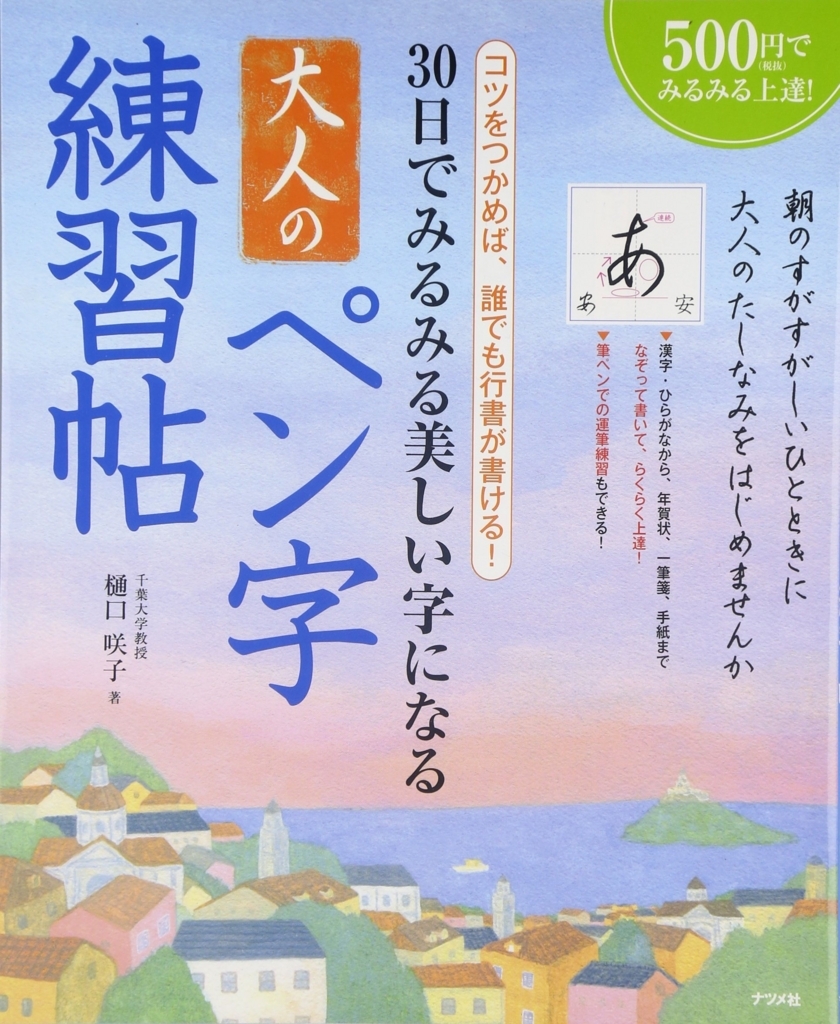
こちらも500円(税別のためワンコインではない)で美文字を練習できる「30日でみるみる美しい字になる大人のペン字練習帖」はナツメ社から2015年11月2日に発売。
■一目置かれる、大人のためのペン字練習帖
行書とは、文字を少しくずし、つなげ気味に書く方法で、楷書に比
べてやわらかく大人っぽい印象の字になります。年賀状や手紙など
で行書が使えれば、きっと一目置かれることでしょう。本書では、
はじめてでも気軽に行書の練習を始めることができます。
■コツをつかめば、誰でも行書が書ける!
本書では、ふだん使っている楷書を行書にするための原則をわかり
やすく解説しました。お手本をなぞりながら練習すれば、誰でも簡
単に行書が書けるようになります。
■楽しみながら練習できる内容
ひらがなやカタカナ、年賀状や手紙でよく使う表現などを豊富に紹
介するのはもちろん、俳句や和歌、古典のお手本も掲載しています
ので、楽しみながら練習することができます。